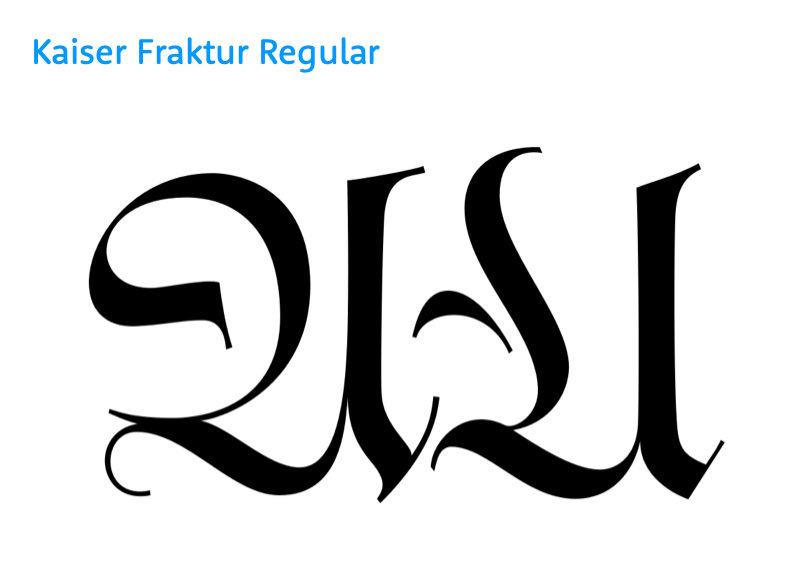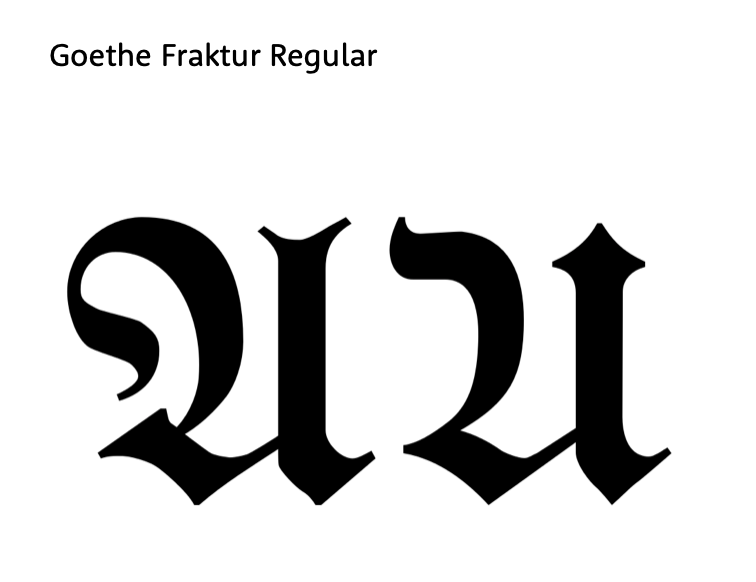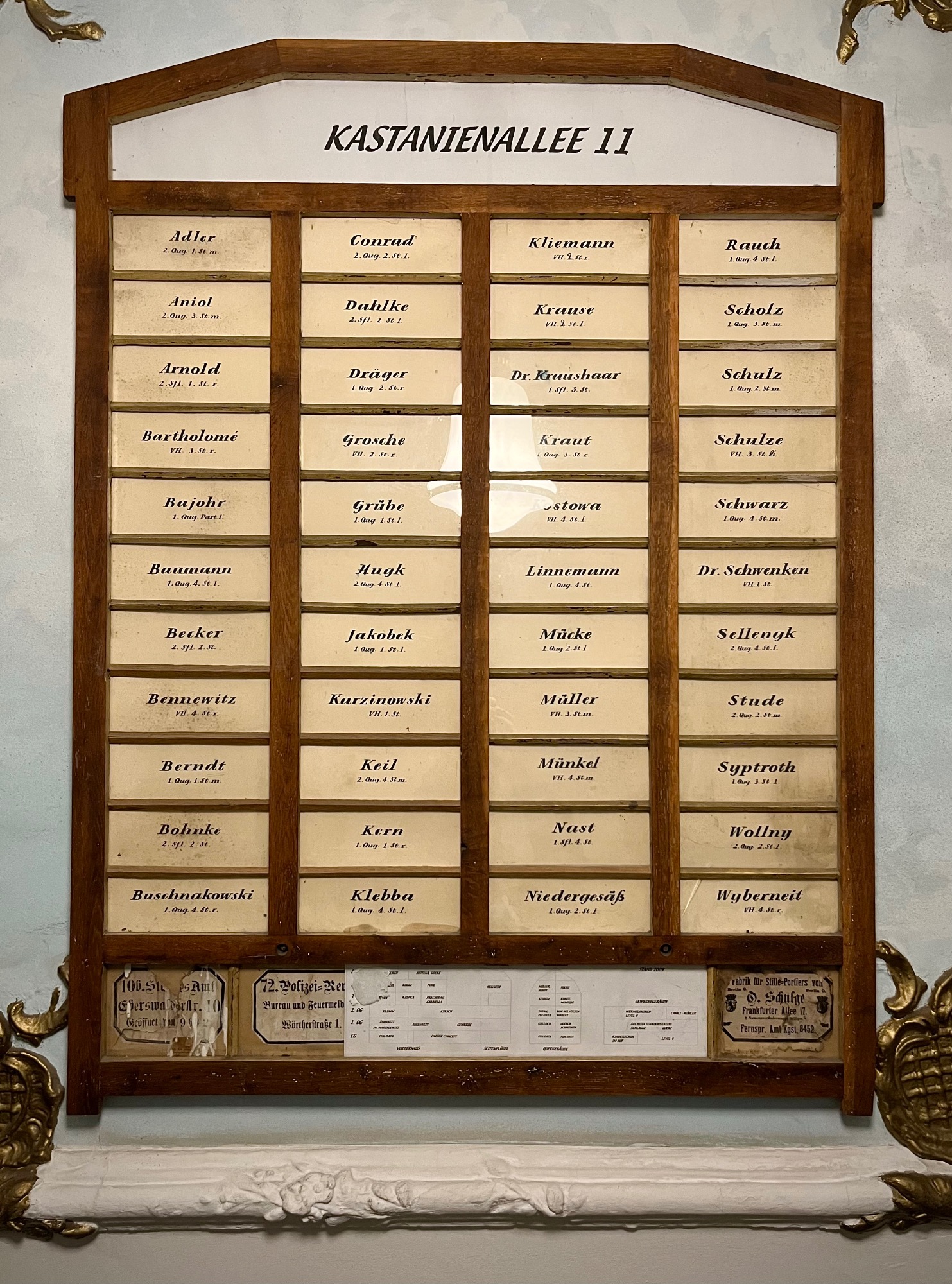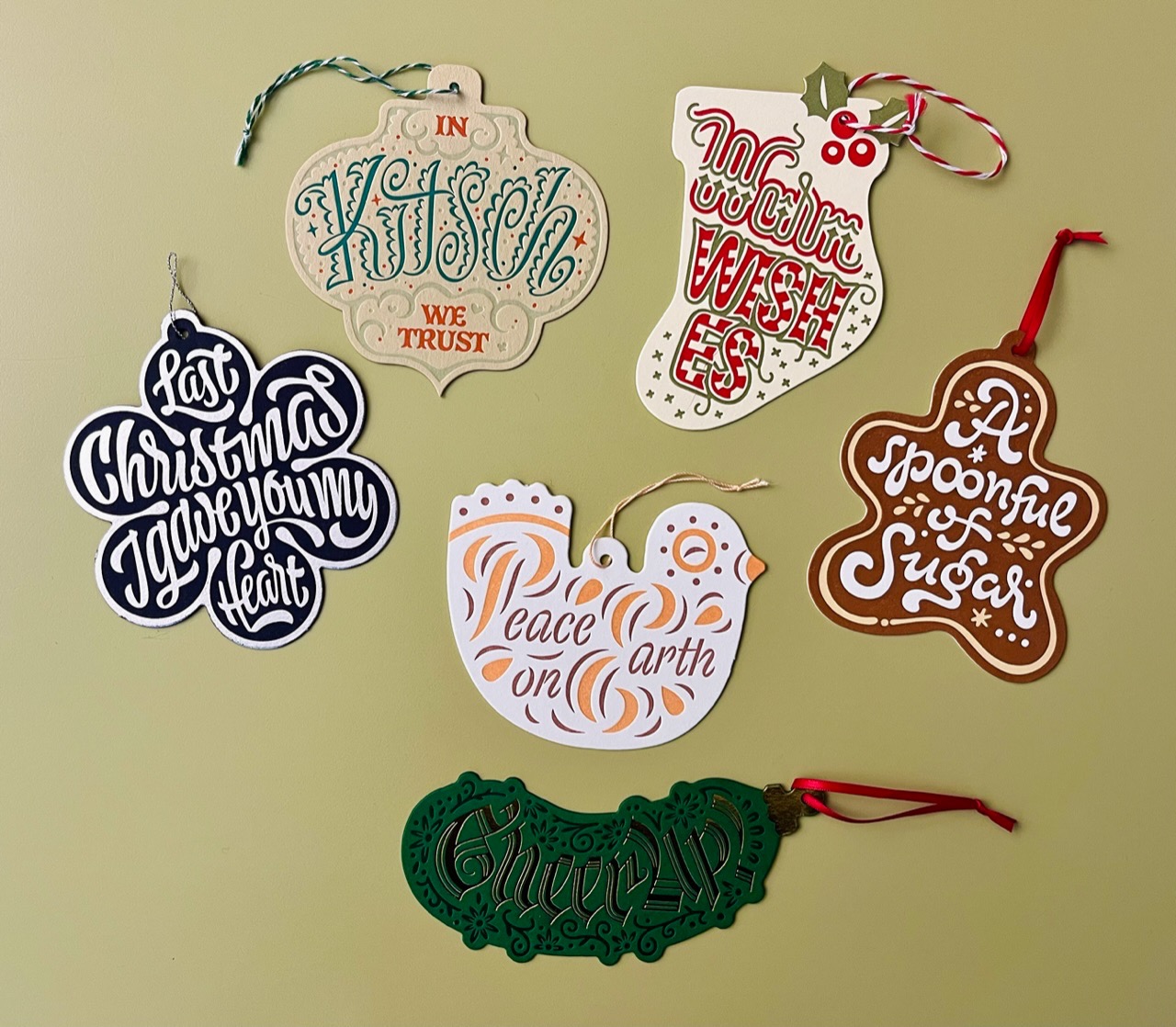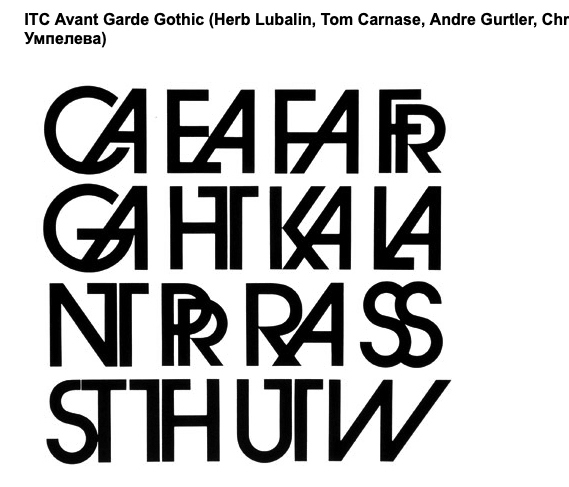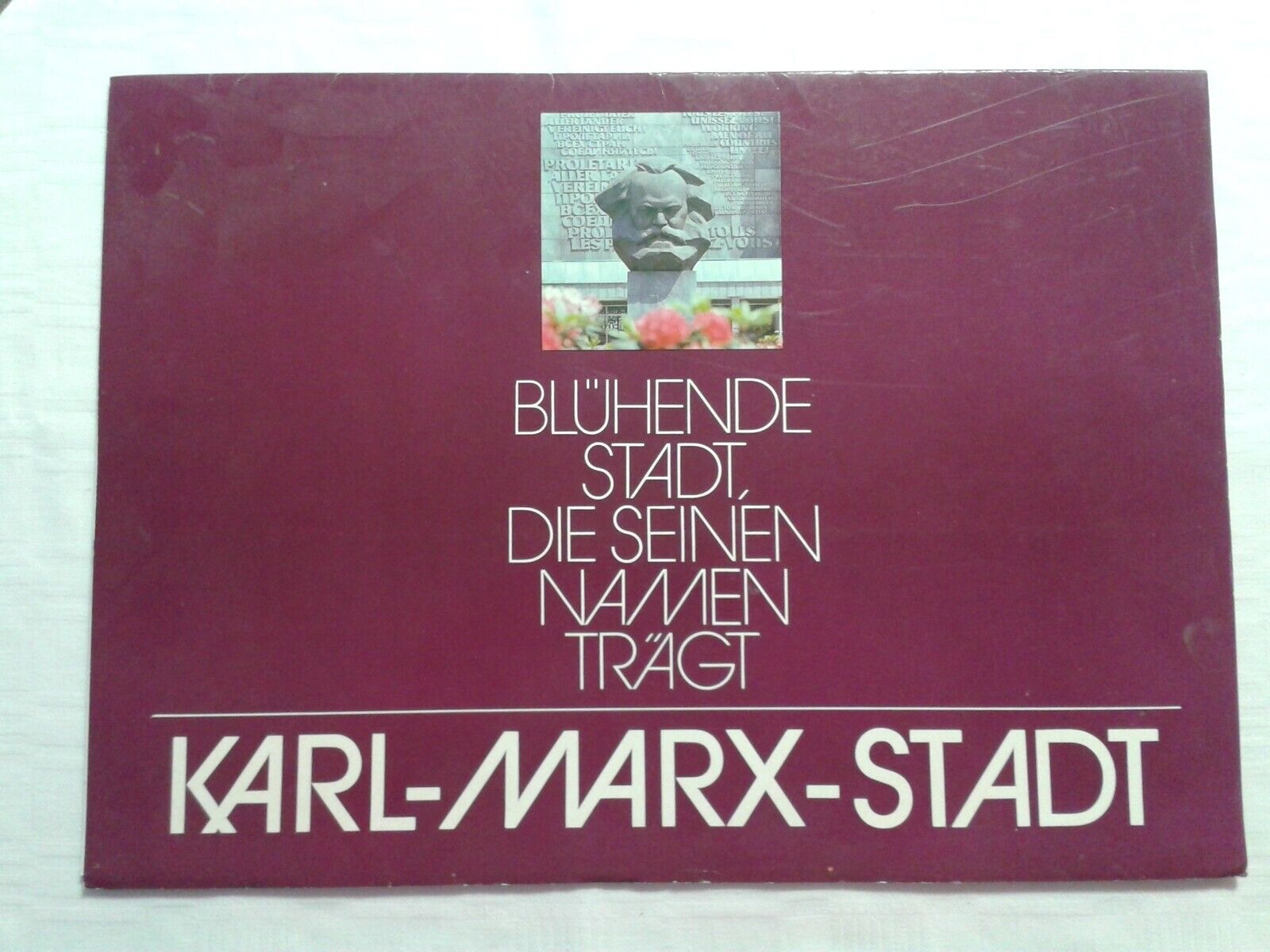
Ich hatte ehrlich gesagt auch meine Mühe damit. Ist ja auch nicht gleich das Erste, was einen zu Weihnachten einfällt. 😬
Ich gar nicht. Und das obwohl ich bei gebrochenen Schriften nicht in Übung bin ... Aber gestürzt wie auf dem Bild ließt es sich natürlich schlechter.
Werden die Weihnachtsgurken nicht im Baum versteckt und wer sie als erstes entdeckt, bekommt ein zusätzliches Geschenk?
jepp. die sogenante Weihnachtsgurke gibts bei uns auch jedes Jahr im Baum.
Ich musste auch kurz überlegen konnte es dann aber gleich entziffern. Hübsch! Bei "Warm Wishes" habe ich länger gebraucht.
Ja nun, zu blöd zum Lesen bin ich auch nicht – erschlossen hat sich mir das wohl schon. Ich wollte nur andeuten, dass die Buchstabengestaltung etwas gewöhnungsbedürftig ist. Gerade das U, das wie ein Fraktur-A daher kommt ...
Ich finde das »geschwungene« U jetzt nicht so untypisch wie es dein Beispiel nahelegt ...
Ich finde die typografische Umsetzung der Karten sehr stimmig und es ist aus meiner Sicht auch nicht dramatisch wenn man sich die Texte »erarbeiten« muss. Es ist ja kein Busfahrplan und Weihnachten hat man »hoffentlich« auch etwas Zeit ...
Das sind auch beides gute Beispiele, wie sich das U vom A unterscheidet: der Schwung kommt von rechts bzw. oben – bei der Gurke kommt er von unten/links wie bei allen gezeigten A-Formen ;-)
Dem will ich auch gar nicht widersprechen – ich finde die auch toll, auch wenn mich das A irritiert :nicken:
Zur Weihnachtsgurke wird hier in Amerika kolportiert, daß nach "alter deutscher Tradition" dasjenige Kind ein extra Geschenk bekommt, welches die Gurke zuerst im Baum entdeckt. Das war mir neu, und deshalb schlug ich es nach. Die häufigste Entstehungsgeschichte besagt, daß ein Geschäftsmann im 19ten Jahrhundert Glasornamente aus Deutschland importiert hat, und sich die Gurken sich als Ladenhüter herausstellten. Er erfand flugs diese niedliche "Tradition", und seitdem darf die Gurke im Weihnachtsbaum nicht fehlen.
Vielleicht ist aber auch diese Geschichte frei erfunden :-?
Wir haben auch so'n Ding im Treppenhaus, ist aber seit Jahren nicht aktualisiert worden … das kam ins Haus, als der letzte Eigentümer überall im Gebäude nachträglich Stuck anbringen ließ (3. Rokoko, Gründerzeit, Jugendstil und Baumarktbarock).
Ich habe es vor Augen
Ich leider auch – immer wenn ich aus dem Schlafzimmerfenster gucke.
Zumauern
Ich hab mir so'n modernes Konzept zugelegt, das heißt »Vorhänge«, wenn ich das richtig erinnere.
»Vorhänge«
... sind aber nie so perfekt licht- und sichtdicht wie eine gut verputzte Steinmauer! ;-)
... oder halt ein guter Rollladen ... ;-)
Ich bin gerade über die Zimula gestolpert – neben einer Version mit Inktraps bietet sie auch eine Variante mit Inkspots! In Thin sieht das wirklich hübsch aus ...
Mich verstört vor allem die KA-Ligatur … naja, eigentlich der inkonsistente Einsatz der Verbindungen mit dem Versal-A durch die »Karl-Marx-Stadt« Zeile hindurch.
Ob man sich die »echte« Ligatur nicht leisten konnte und improvisieren musste?
Die spezielleren Ligaturen durften vielleicht nicht in den Ostblock exportiert werden.
Fielen unter die bekannten Avantgarde-Sanktionen, hmm, hmm … ist doch die Avantgarde, oder? Könnte aber auch nach Vorbild handgezeichnet sein, und die originale KA-Kombination erschien zu mutig und wurde deshalb etwas abgemildert, da zu stark gekreuzt?!
Schreiben noch älter als bisher gedacht!
[...] Homo sapiens groups drew, painted and engraved non-figurative signs from at least ~42,000 bp and figurative images (notably animals) from at least 37,000 bp [...] we suggest how three of the most frequently occurring signs—the line <|>, the dot <•>, and the <Y>—functioned as units of communication. [...] in close association with images of animals the line <|> and dot <•> constitute numbers [...] the <Y> sign, one of the most frequently occurring signs in Palaeolithic non-figurative art, has the meaning <To Give Birth>. [...]
Man kann noch weitere Schlüsse ziehen. Wenn das <Y> für Geburt – aus eins werden zwei – steht, so sind der Ausgangszustand unten und das Resultat oben platziert, d.h. eine Orientierung alt-neu = unten-oben. Das Neuhinzugekommene überlagert das Alte. Diese grundlegenden Denkprozesse sind dann damals wie heute gleich im Gehirn organisiert.